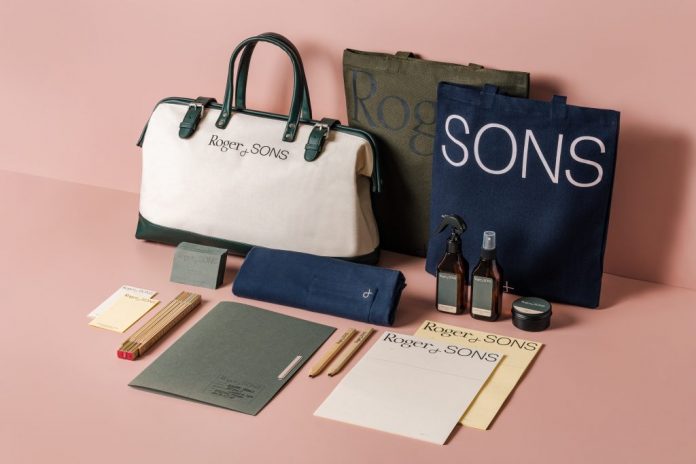
The Type Directors Club Awards : promouvoir l’excellence de la typographie
Foreign policy, Singapour
Roger&Sons est une entreprise de menuiserie familiale. Fondé par leur père, l’établissement est aujourd’hui dirigé par trois frères. Dans les ateliers, des charpentiers chevronnés travaillent aux côtés de jeunes menuisiers, expérimentant des techniques modernes et repoussant les limites de l’artisanat du bois. Afin de refléter le changement de direction, le studio Foreign Policy conçoit une nouvelle identité graphique. Le logotype affiche deux typographies : tandis que « Roger » s’inscrit en gc16, une monochasse à empattements avec une allure vintage dessinée par Mads Wildgaard, « Sons » arbore la GT America, une linéale contemporaine conçue par Noël Leu et Seb McLauchlan. Entre les deux, l’esperluette apparaît dans une version moderne et simplifiée. Ce nouveau logotype habille l’ensemble des éléments de communication de l’entreprise, du papier à en-tête au stylo en passant par une gamme de soins pour le bois. Le langage visuel incarne l’esprit énergique de la marque et cible une nouvelle génération de consommateurs.
→ Catégorie : Identité
→ Client : Roger&Sons
→ Typographie : GT America et gc16